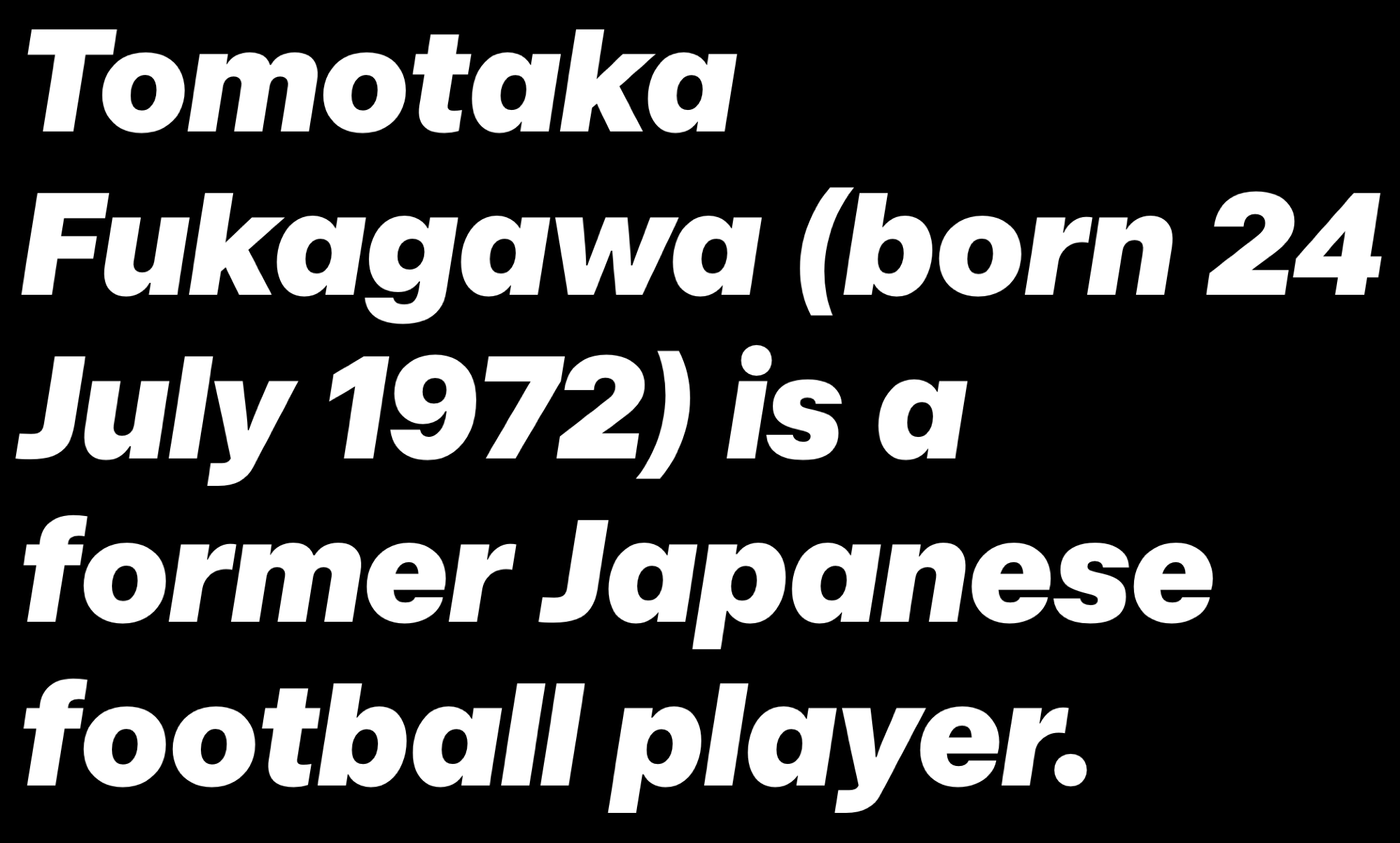
Universal Sans ist eine Groteskschrift des neuseeländischen Gestalters Briton Smith und erschien Ende 2019 über dessen Label Family Type. Die Schrift baut auf dem Erbe erfolgreicher Groteskschriften wie Akzidenz Grotesk und Helvetica auf und setzt die verschiedenen Ausprägungen dieses Schriftstils als variable Schrift mit ganzen sechs Gestaltungsachsen (Strichstärke, Weite, Mittellänge, Tintenfalle, Strichabschlüsse, Proportionen) um. Bei der Lizenzierung geht man dabei neue Wege: Interpolation und Buchstabenvarianten können über die zugehörige Website ausgewählt und dann als statische Fonts lizenziert und heruntergeladen werden.